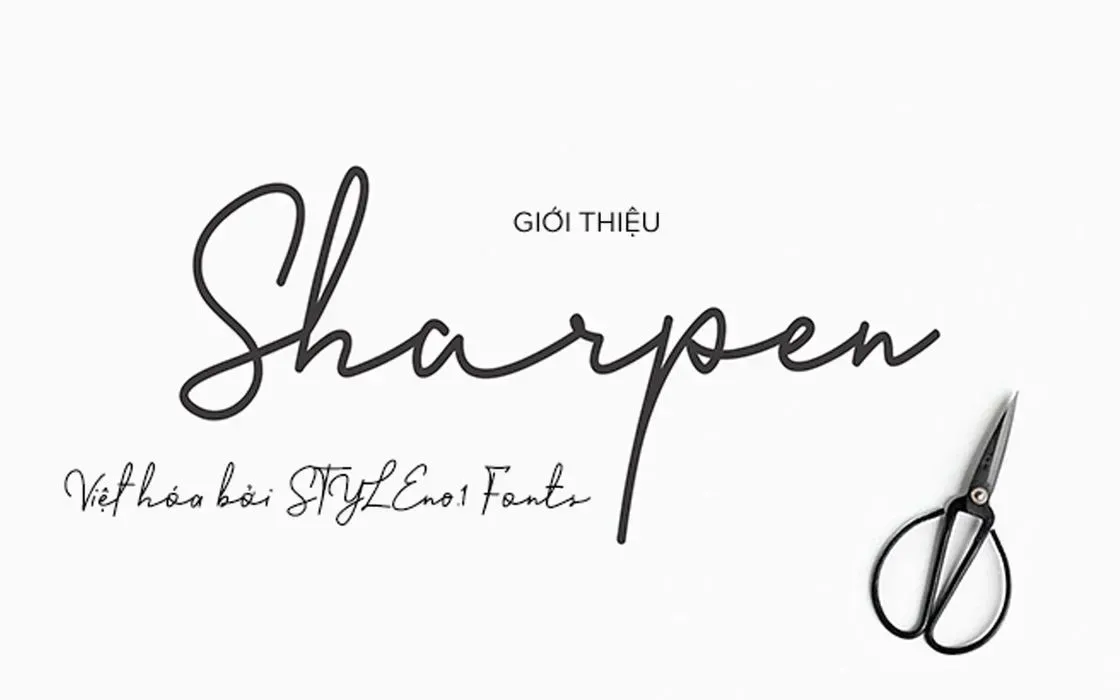
Font chữ SVN Sharpen – Viết tay, Mềm mại & Việt hóa đầy đủ
SVN Sharpen là một font chữ viết tay (handwritten) mang phong cách tự nhiên, mềm mại và gần gũi, tái hiện những nét chữ tay mộc mạc nhưng vẫn tinh tế, gọn gàng. Font mang đậm tính cá nhân, với các ký tự hơi nghiêng nhẹ, có độ rung tự nhiên như khi viết bằng bút bi hoặc bút dạ lên giấy.
Từng chữ cái trong SVN Sharpen được thiết kế nhẹ nhàng, thanh thoát, phù hợp với các thiết kế cần gợi cảm giác chân thành, nhẹ nhàng và cảm xúc. Đặc biệt thích hợp cho: thư mời, blog cá nhân, thiệp cảm ơn, nhật ký sáng tạo, bao bì handmade, hoặc thương hiệu mang phong cách thủ công.
Font gốc Sharpen Script được thiết kế theo xu hướng casual handwriting, mô phỏng chữ viết tay đời thường nhưng được tinh chỉnh kỹ lưỡng để đảm bảo tính nhất quán và dễ đọc. Đây là phong cách thường thấy trong các thiết kế gần gũi với người dùng, nơi cần sự kết nối cảm xúc.
Phiên bản Việt hóa bởi SVN Fonts đã được bổ sung đầy đủ dấu tiếng Việt, đồng thời giữ nguyên độ mềm mại, liền mạch của từng chữ cái, giúp font hoạt động mượt mà trên các phần mềm thiết kế như Photoshop, Illustrator, Canva, PowerPoint…
Nếu bạn đang tìm một font viết tay nhẹ nhàng, tự nhiên nhưng vẫn trau chuốt, SVN Sharpen là lựa chọn lý tưởng để thể hiện cảm xúc chân thật, vẻ đẹp thủ công và tính cá nhân trong từng thiết kế.